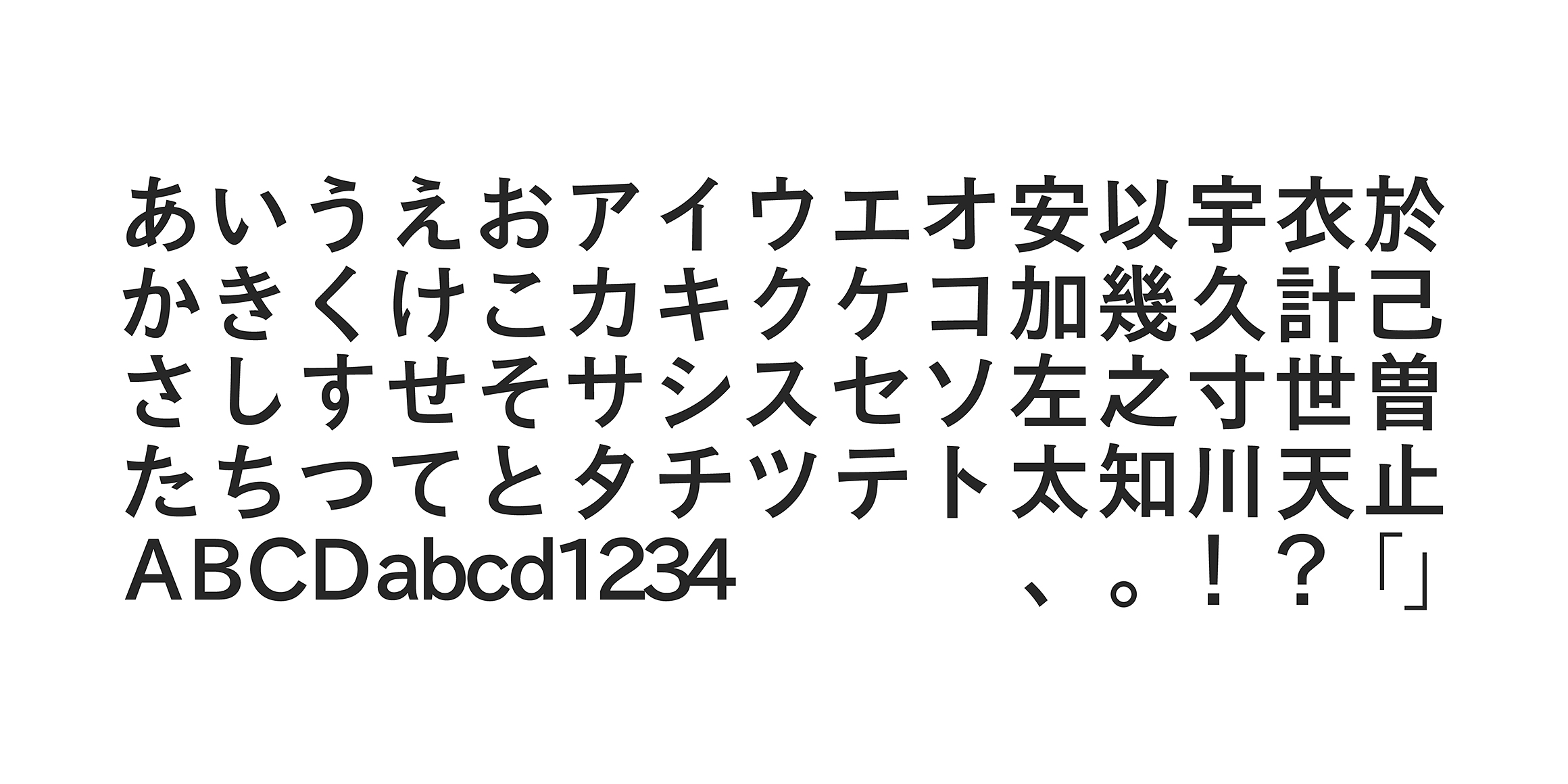
AR FangXinShuH7C95GB
분류 Sans
AR FangXinShu는 간결하고 단단한 골격을 유지하면서 동시에 편안함과 우아한 인상을 준다. 제목은 물론 본문에서도 인식성이 뛰어나 유저에게 좋은 사용자 경험을 선사할 수 있을 것으로 기대한다.
폰트명 중간에 표기된 'C'는 Condensed(폭이 좁은)를 의미하며 뒤의 숫자는 좁혀진 폭의 정도를 나타낸다.
폰트명 뒤에 붙은 GB라는 표기는 간체의 문자코드를 뜻한다. 간체란 중국에서 주로 사용하며 필획을 줄이고 자형을 간단하게 만든 한자다. 대만, 홍콩, 마카오 등에서 사용하는 번체(B5)와는 달라 잘못 적용할 경우 글립이 제대로 표기되지 않거나 다른 글립으로 표기되는 문제가 발생할 수 있다.